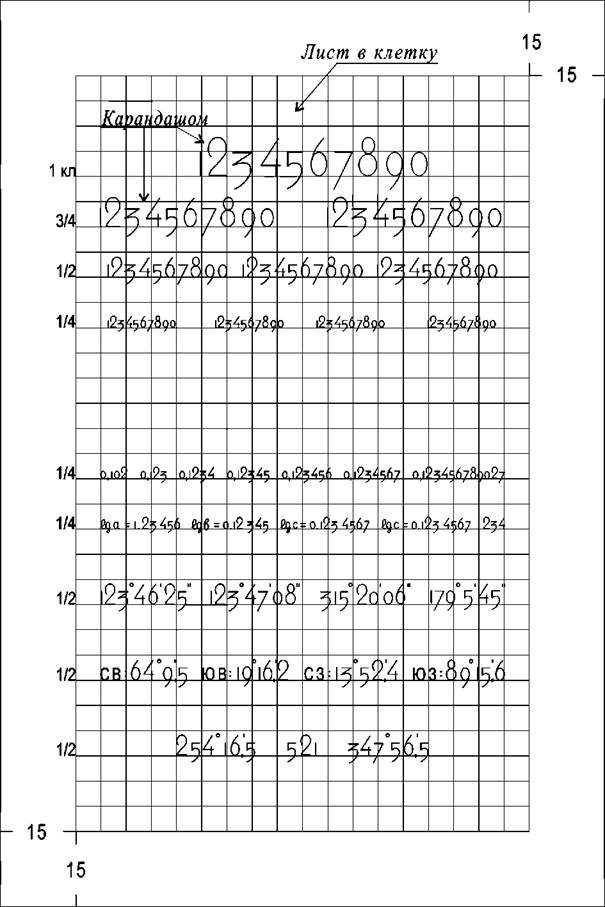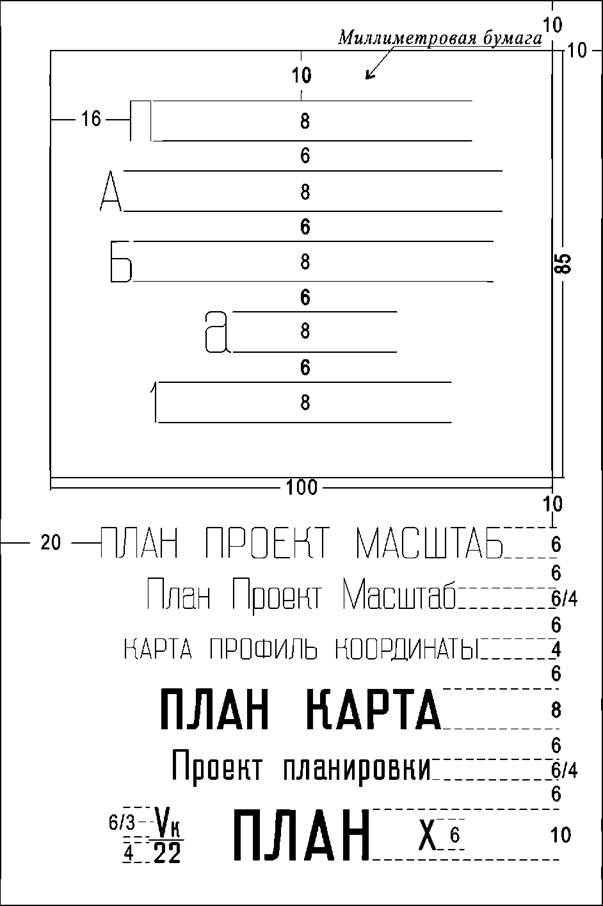
Картографический полужирный шрифт
Шрифты Цель — приобрести теоретические знания и практические навыки по шрифтовой графике. Общие сведения. Графическое начертание букв и цифр называется шрифтом. Картографические планы и карты, а также графические материалы в землеустроительном и кадастровом производстве несут большую информационную нагрузку в виде различных подписей. Эти подписи, выполненные с применением нескольких видов шрифтов, заключают в себе не только количественную, но и качественную информацию. К основным, наиболее применяемым шрифтам, относятся: Картографический, рубленый, курсив. На землеустроительных проектах и планах чаще всего используют шрифты: рубленый, обыкновенный и стандартный. При компьютерном оформлении графических материалов применяют специализированные машинные шрифты, которые в данном пособии не рассматриваются. Буквы алфавита состоят из отдельных элементов и имеют 5 основных показателей: высоту (Н), ширину (В), толщину штриха (Т), радиус закругления (R) и наклон. Показатели связаны между собой определенной пропорциональной зависимостью, характерной для каждого шрифта. По величине отношения ширины букв к высоте шрифты делят на узкие, нормальные и широкие. По толщине элементов — на остовные (тонкие) и наливные; группа наливных шрифтов выполняется в светлом, полужирном и жирном начертаниях. Шрифты различают также по наклону — прямые и наклонные (вправо и влево). При написании слов прописные (заглавные) буквы обычно пишут на 1/3 — 1/2 выше строчных. Расстояние между словами принимают равными двойной ширине букв. Промежутки между буквами в словах составляют, как правило, 1/2 ширины нормальной буквы. При сочетании букв, имеющих наклонные элементы (ГА, ТА, ГУ, УА и др.), следует уменьшать промежутки между ними. Изменение интервалов в этих случаях устанавливают так, чтобы площади просветов между буквами зрительно были одинаковыми. При высоте шрифта 3 мм и менее буквы в словах проставляют с интервалом в 1 мм для улучшения читаемости. Требования. Строго соблюдать начертание букв, наклон, промежутки между буквами и словами. Задание 5. Рубленый шрифт а) Рубленый остовный шрифт Особенности шрифта. Шрифт прямой. Все элементы букв и цифр имеют одинаковую толщину (0,1—0,2 мм). Отношение ширины букв типа П, Н, И и др. к высоте равно 1:2. Буквы Ж, М, Ф, Ш, Щ, Ы, Ю, Д вычерчивают в полтора раза шире нормальных букв. Строчные буквы а, б, е, р, у, ф имеют начертание, отличающееся от соответствующих им прописных букв. Величина выносных элементов у букв б, р, у, ф составляет половину высоты строки. Радиус закругления у букв равен 1/8 ее высоты.
Рис 8. Вычислительные цифры Вычерчивание шрифта. Образец рубленого остовного шрифта представлен на рис. 9. Работу выполнить в соответствии с макетом (рис 10.). Вначале вычертить на миллиметровой бумаге алфавит по группам, указанным на образце. Построить буквы и цифры карандашом, располагая их симметрично относительно оси форматки, затем вычертить тушью чертежным пером методом наращивания. В таком же порядке выполнить слова, состоящие из прописных (заглавных) букв, а также из сочетания прописных и строчных букв. При выполнении слов крупного размера (5 мм и более) сделать на строке разметку по ширине букв и промежутков. При написании слов мелкого размера (менее 5 мм) разграфку выполнить через суммарное расстояние, равное ширине буквы и интервала. б) Рубленый полужирный шрифт. Особенности шрифта. Принципиальное отличие рубленого полужирного шрифта от остовного заключается в толщине элементов букв, которая равна 1/8 от высоты буквы. Все остальные характеристики этих шрифтов одинаковы. В работе (рис. 10) выполнить соответствующие надписи по образцу шрифта (рис. 11). Вычерчивание шрифта. При написании слов крупного размера рубленым полужирным шрифтом вначале построить буквы в две линии, получая шрифт в прозрачном начертании, а затем выполнить заливку. При вычерчивании слов мелкого размера буквы вычертить в остовном начертании, а затем, применяя метод наращивания, увеличить толщину элементов до нужного размера. Для ослабления зрительной иллюзии горизонтальные элементы вычертить на 0,1 мм тоньше вертикальных. Картографический полужирный шрифт предлагается для самостоятельного изучения. Специального задания по этому шрифту не предусмотрено, но в работе «Часть Картографической карты» (см. далее) названия населенных пунктов и некоторые пояснительные надписи должны быть выполнены Картографическим полужирным шрифтом. Поэтому образец шрифта и его основные характеристики даны в методических указаниях (рис. 12).
Рис . 9. Образец рубленого остовного шрифта
Рис. 10. Рубленый шрифт
Рис. 11. Образец рубленого полужирного шрифта
Рис. 12. Картоографическии полужирный
Особенности шрифта. Толщина основного элемента равна 1/8 высоты буквы. Отношение ширины нормальной буквы к высоте равно 1:2. Ширина букв Д, Ж, М, Ф, Ш, Щ, Ы, Ю на половину больше, чем у нормальных. Строчные буквы а, б, е, р, у, ф отличаются по своему начертанию от соответствующих прописных букв. Радиус закругления составляет 1/4 высоты. При написании букв и слов Картографическим полужирным шрифтом следует руководствоваться ранее изложенной методикой (см. рубленый и рубленый полужирный шрифт). Задание 6. Курсив остовный Особенности шрифта. Шрифт имеет наклон 1:3. Толщина всех букв одинакова и соответствует 0,1-0,2 мм. Отношение ширины к высоте у нормальных букв равно 4:7. Ширина прописных букв Д, Ж, М, Ф, Ш, Щ, Ы, Ю в полтора раза больше, чем у нормальных. Все строчные буквы (кроме О) отличаются по своему начертанию от заглавных. Шрифт имеет подсечки (1/7 высоты буквы). У прописных букв — двухсторонние, у строчных — односторонние (сверху, влево от прямого элемента). Округлые буквы имеют в основе овал, а элементы строчных букв внизу заканчиваются овальными ластовицами. Вычерчивание шрифта. Работу вычертить в соответствии с макетом (рис. 13) по образцу данного шрифта (рис. 14 — заглавные буквы, рис. 15 — строчные). Для проработки алфавита построить наклонную сетку. Расстояния между линиями сетки составляют 1 или 2 мм. Последовательность выполнения работы аналогична заданию № 5 Рубленый шрифт. При выполнении букв остовного курсива особое внимание следует обратить на правильное построение овалов и вычерчивание подсечек. Округлые буквы рекомендуется вычерчивать выше остальных примерно на толщину элемента вверх и вниз от строки, чтобы они не казались меньше рядом расположенных прямых букв. Задание 7. Обыкновенный шрифт Особенности шрифта. Шрифт прямой, контрастный, с подсечками. Отношение толщины основного элемента к соединительному равно 5:1.
Рис. 13. Курсив
Рис . 14. Образец курсива (заглавные буквы)
Рис . 15. Образец курсива (строчные буквы)
Рис. 16 Образец обыкновенного шриф та
Рис. 17. Обыкновенный шриф т Толщина основного элемента составляет 1/6 высоты буквы. Отношение ширины нормальной буквы к высоте равно 4:6. Имеются «полуторные» буквы: Ш, Щ, М, Д, Ж, Ю, Ы, Ф. Шрифт имеет линейные подсечки, выступающие на половину толщины основного элемента в обе стороны. Тонкие элементы заканчиваются подсечкой в виде треугольника или каплевидной точки. Для букв Г, Т, Б, Е характерно наличие своеобразного элемента — ластовицы, для букв Ц, Щ, Д — родственного с ним элемента — подковки, у букв С, Э, 3 — стрелообразного элемента. Строчные буквы а, б, е, р, у, ф, с отличаются по начертанию от соответствующих заглавных букв. Величина выносных элементов у букв б, р, у, ф составляет примерно половину высоту строки. Промежутки между буквами — не менее половины ширины нормальной буквы.
Вычерчивание шрифта. Работу выполнить в соответствии с Рис. 18 Задание 8. Стандартный шрифт Особенности шрифта. Шрифт пишут с наклоном 75°; осно-ными элементами у букв являются прямой штрих и части овала. Отношение ширины нормальной буквы к высоте равно 6:10.
Рис. 19. Образец стандартного шриф та
Рис. 20. Стандартный шриф т Толщина всех элементов букв и цифр в этом шрифте одинакова и равна 1/10 от высоты прописной буквы. Расстояние между буками составляет величину, равную 2/10 от высоты; между буквами, соседние линии которых не параллельны между собой (например, ГА, ТА и др.), это расстояние может быть уменьшено наполовину. Строчные буквы а, б, в, г, д, е, р, и, й, п, ш, щ, ц, т, ф, у имеют иное начертание, чем однозначные прописные. Буквы б, в, д, имеют надстрочные элементы, а буквы р, у, ф — подстрочные, которые выносят за пределы строки до размера прописных букв. Высота строчных букв составляет 7/10 от высоты прописных. Для данного технического шрифта Государственным стандартом (ГОСТ 2,304-81) установлены следующие размеры: 40; 28; 20; 14; 10; 7; 5; 3,5; 2,5 и 1,8 мм для прописных букв. Для строчных букв дополнительно установлен размер 1,3 мм. Выполнение шрифта. В отличие от картографических шрифтов стандартный шрифт не вычерчивается способом наращивания, а пишется специальными перьями «Редис» или фломастерами. Рекомендуется проработать буквы по образцу шрифта (рис. 19) на тетради в косую линейку, а затем выполнить работу на форматке в соответствии с макетом (рис. 20). Для сохранения наклона шрифта следует провести карандашом вспомогательные линии через 1 см.